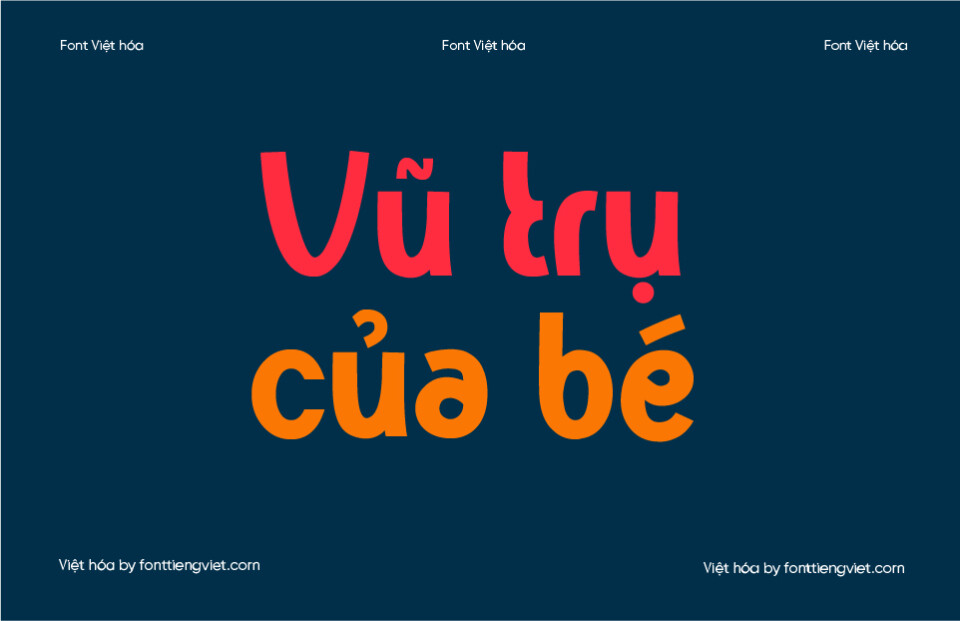
Font Việt hóa 1FTV Round Rope
Giới thiệu về bộ Font Việt hóa 1FTV Round Rope đầy sáng tạo
Trong thế giới đồ họa hiện đại, việc tìm kiếm một Font Miễn Phí có phong cách vừa mềm mại vừa tinh tế luôn là ưu tiên hàng đầu của các bạn học sinh và giáo viên. Font Việt hóa 1FTV Round Rope chính là giải pháp hoàn hảo, mô phỏng hình dáng những sợi dây thừng uốn lượn đầy nghệ thuật. Bộ font này không chỉ giúp bài thuyết trình trở nên sinh động mà còn mang lại cảm giác thân thiện, gần gũi trong các dự án học đường. Nhờ quá trình Việt hóa chỉn chu, người dùng có thể hoàn toàn yên tâm sử dụng đầy đủ các dấu câu tiếng Việt mà không lo lỗi hiển thị hay mất nét chữ.
Những ưu điểm nổi bật của Font Việt hóa 1FTV Round Rope trong giáo dục
Thiết kế bo tròn an toàn và hiện đại
Đúng như tên gọi, Font Việt hóa 1FTV Round Rope sở hữu các đường nét bo tròn mượt mà, tạo cảm giác an toàn và dễ chịu cho mắt người xem. Đây là lựa chọn lý tưởng để thiết kế tiêu đề bài giảng, bìa sổ tay hoặc các biển báo trang trí trong lớp học. Sự kết hợp giữa cấu trúc dây thừng và độ dày nét chữ vừa phải giúp thông tin truyền tải rõ ràng nhưng vẫn giữ được cá tính riêng biệt.
Khả năng ứng dụng linh hoạt trên nhiều nền tảng
Cách sử dụng và kết luận về Font Việt hóa 1FTV Round Rope
Để tối ưu hóa vẻ đẹp của Font Việt hóa 1FTV Round Rope, bạn nên kết hợp nó với các tông màu trung tính hoặc màu sắc thiên nhiên để làm nổi bật chất liệu “dây thừng”. Đây chắc chắn là một công cụ hỗ trợ đắc lực cho cộng đồng yêu thiết kế tại Việt Nam. Đừng bỏ lỡ cơ hội tải về Font Miễn Phí, Font Việt Hóa, Font Việt hóa 1FTV Round Rope để làm mới kho tài nguyên sáng tạo của mình ngay hôm nay.